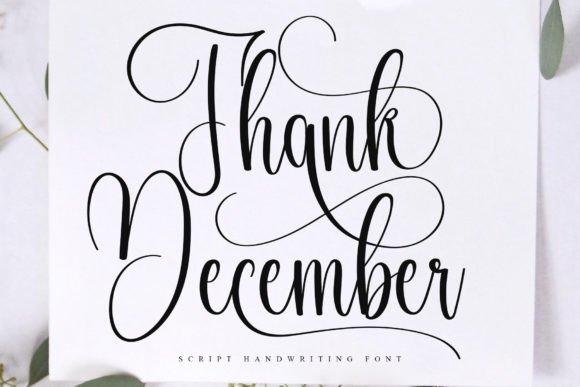
Thank December
Thank Decemberのような高品質の素材をお探しの場合、このプレミアムパッケージはクリエイティブなプロジェクトに素晴らしい選択です。
POD(オンデマンド印刷)製品、結婚式の招待状、またはソーシャルメディアのグラフィックを作成している場合でも、Thank Decemberは理想的です。